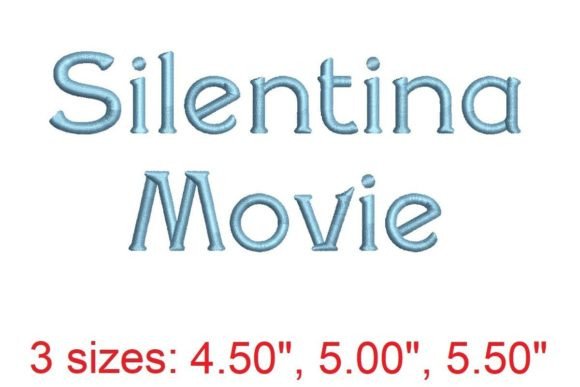
Silentina Movie Embroidery Font
適切なデザイン要素を見つけるのは難しい場合がありますが、Silentina Movie Embroidery Fontは作品を即座に引き立てる優れたコレクションを提供します。
POD(オンデマンド印刷)製品、結婚式の招待状、またはソーシャルメディアのグラフィックを作成している場合でも、Silentina Movie Embroidery Fontは理想的です。